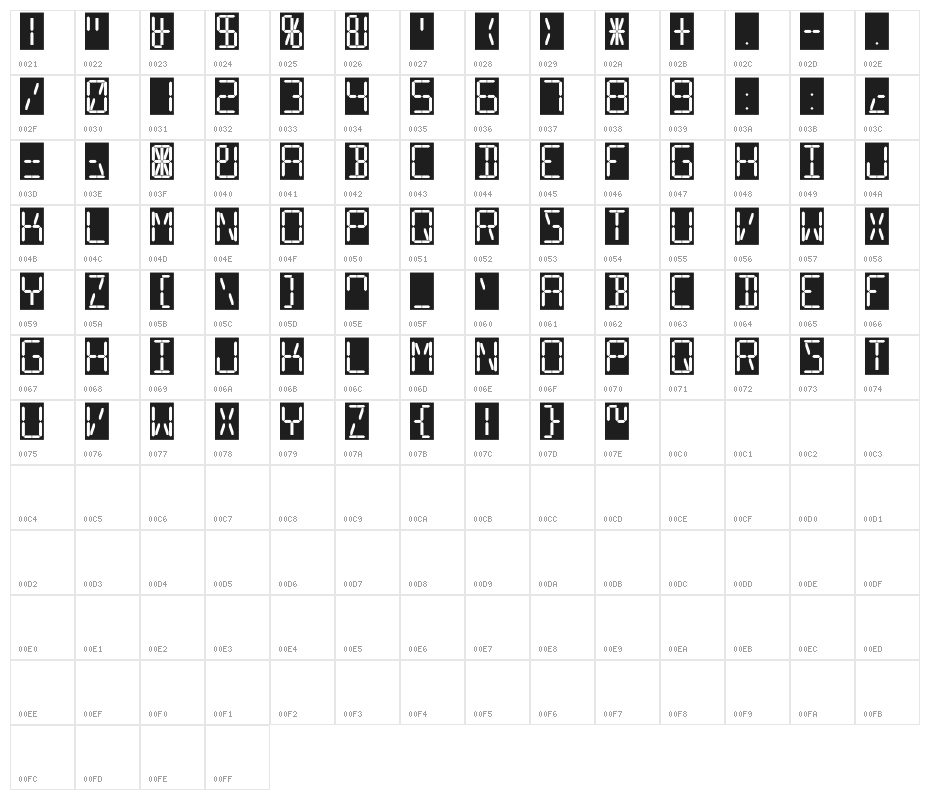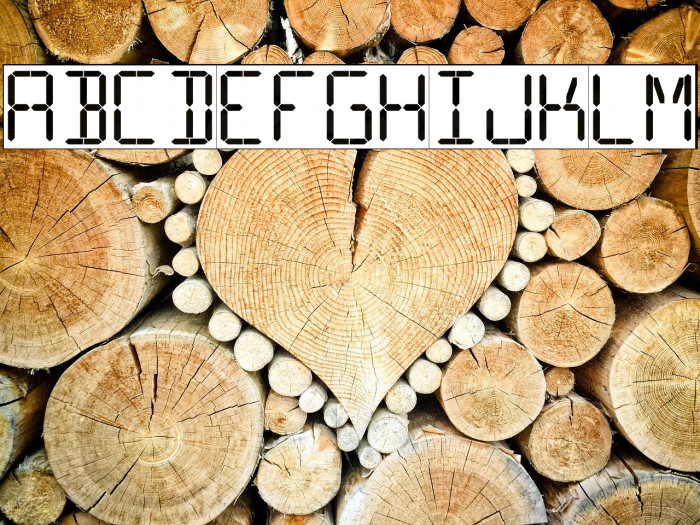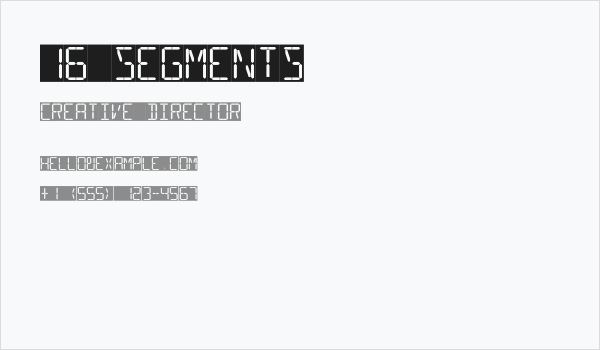
16 Segments Font
| Caso d'uso | Headlines, Logos, Digital displays |
| Progetti proposti | Ideal for digital interfaces, tech-themed designs, electronic device displays, and futuristic branding. |